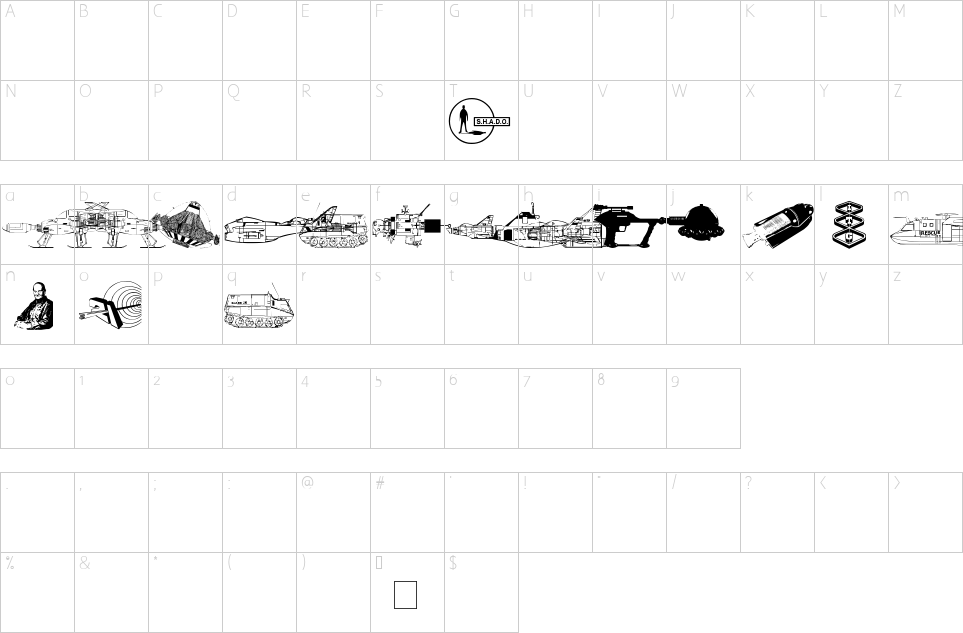
Anderson UFO Font é uma fonte única e inovadora desenvolvida por Steve Ferrera. Perfeita para designers que procuram algo diferente e versátil, essa fonte é ideal para criar gráficos impactantes e uma variedade de aplicações digitais. Com seu design criativo, a fonte Anderson UFO não apenas adiciona um toque especial a seus projetos, mas também contribui para a diversidade e originalidade dos elementos visuais. Atualmente disponível em versões para Windows e Mac, Anderson UFO é um recurso gráfico inestimável para quem busca dar um novo impulso aos projetos digitais. Desde o primeiro download, já foram mais de 5.389 downloads dessa fonte excepcional, demonstrando o quanto ela é apreciada e valorizada pelos profissionais do design.